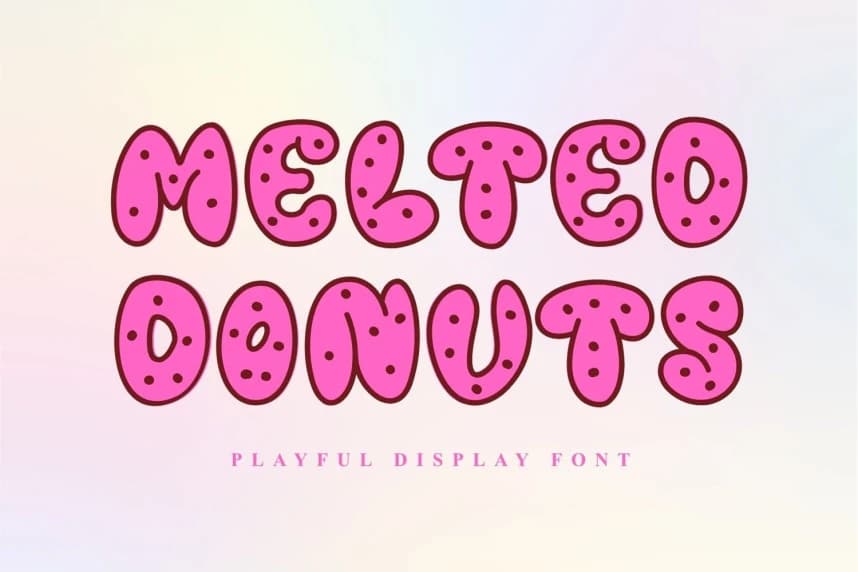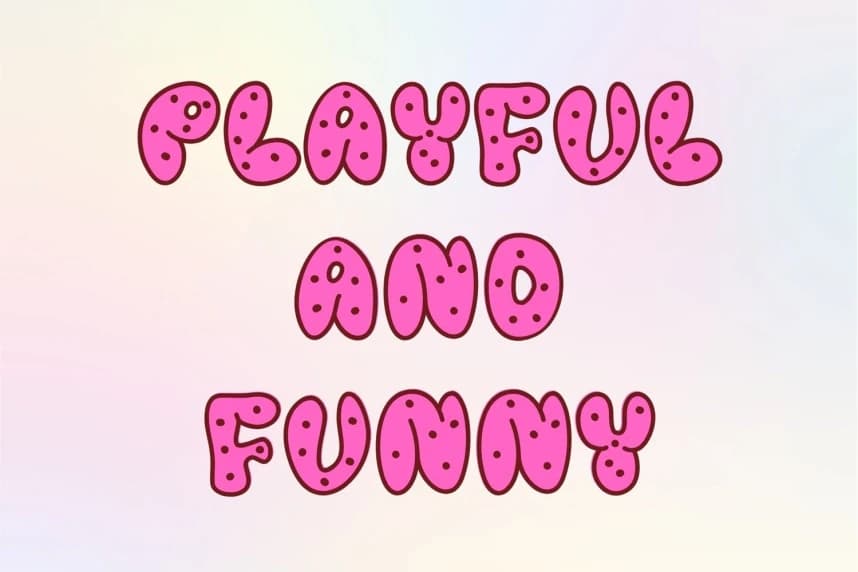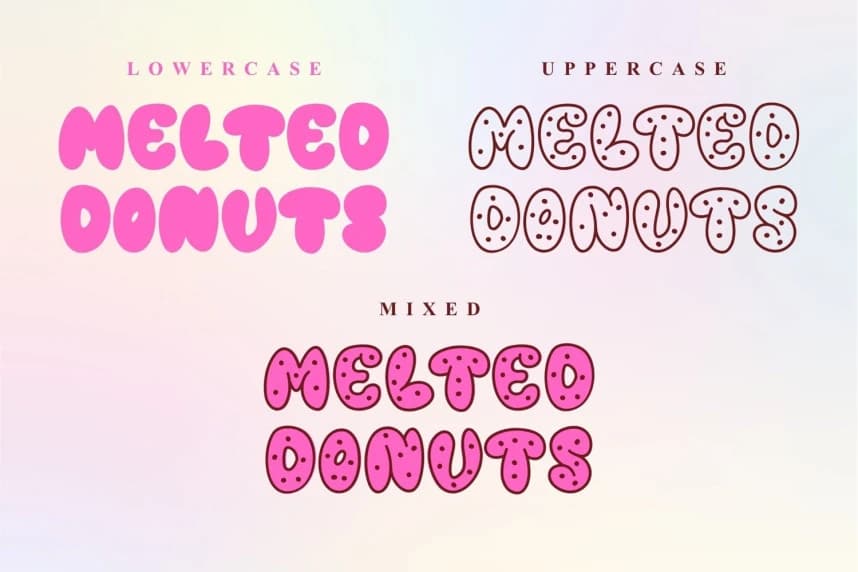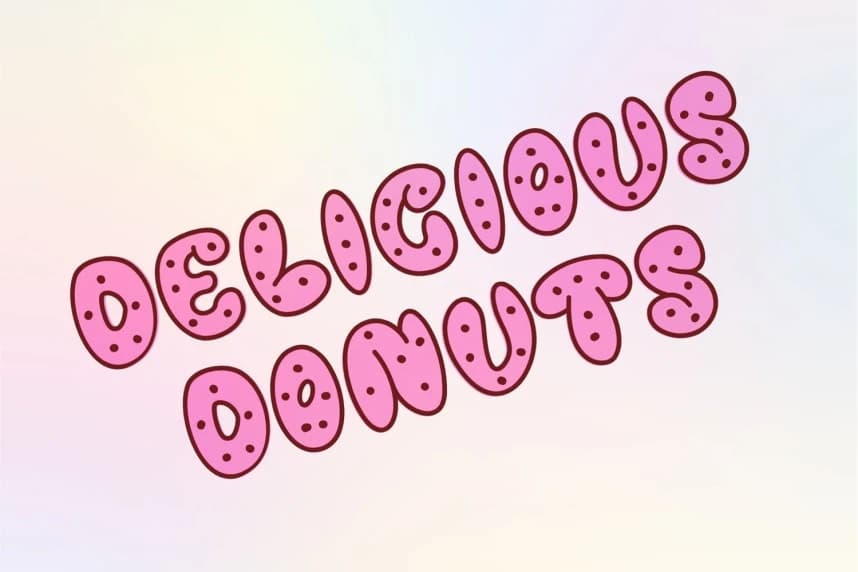
Melted Donuts Font
Melted Donuts Font, yaratıcı projelere neşeli ve ilgi çekici bir görsel kimlik kazandırmak üzere tasarlanmış eğlenceli bir gösteri yazı tipidir. Donut şekillerinden esinlenen yumuşak, yuvarlak harf biçimleri ve dekoratif serpiştirme benzeri detaylar içerir.
Melted Donuts Font, yaratıcı projelere neşeli ve etkileşimli bir görsel kimlik kazandırmayı amaçlayan eğlenceli bir gösteri yazı tipi. Donut şekillerinden ilham alan yumuşak, yuvarlak harf biçimleri ve dekoratif serpiştirme benzeri ayrıntılar içerir